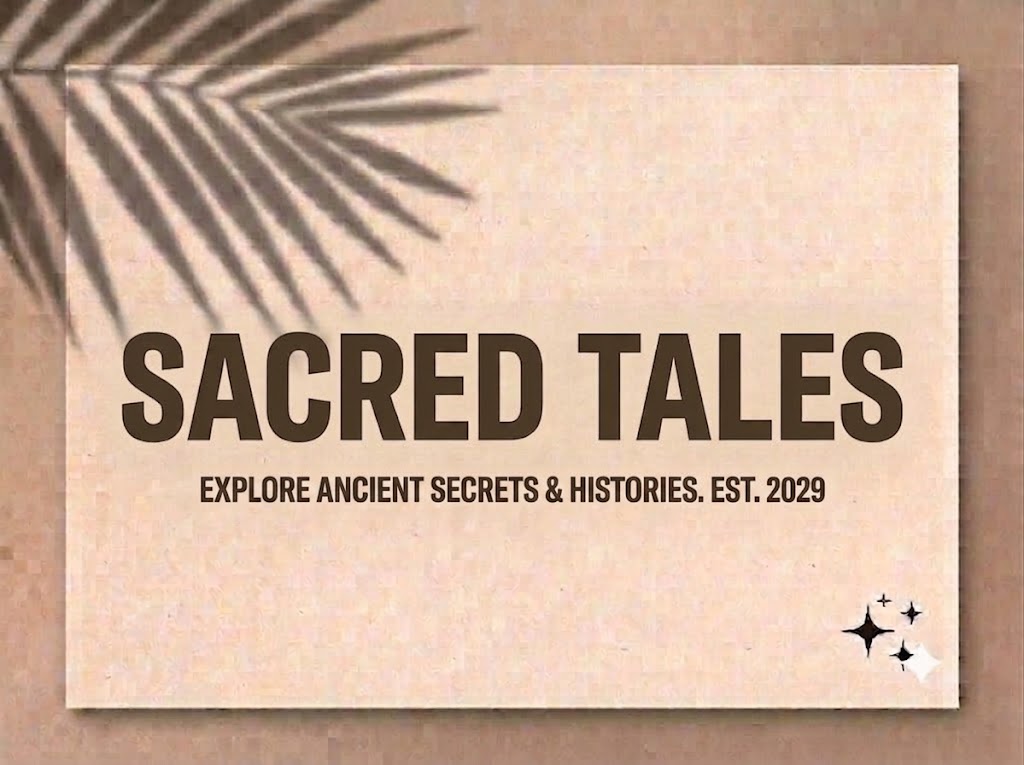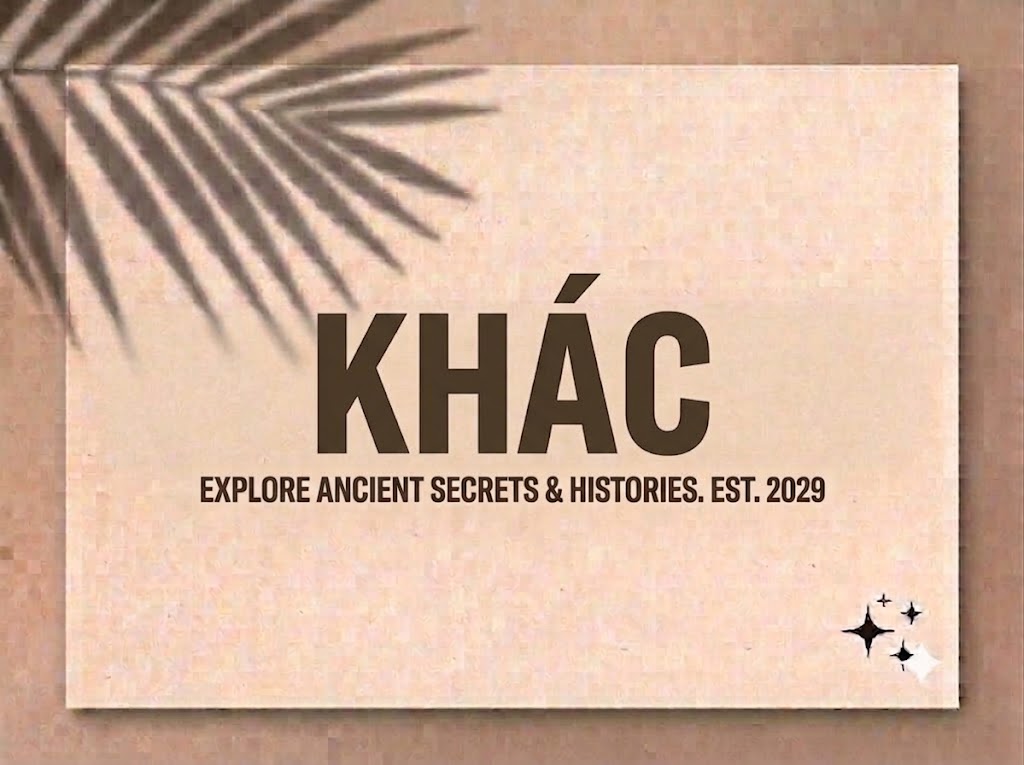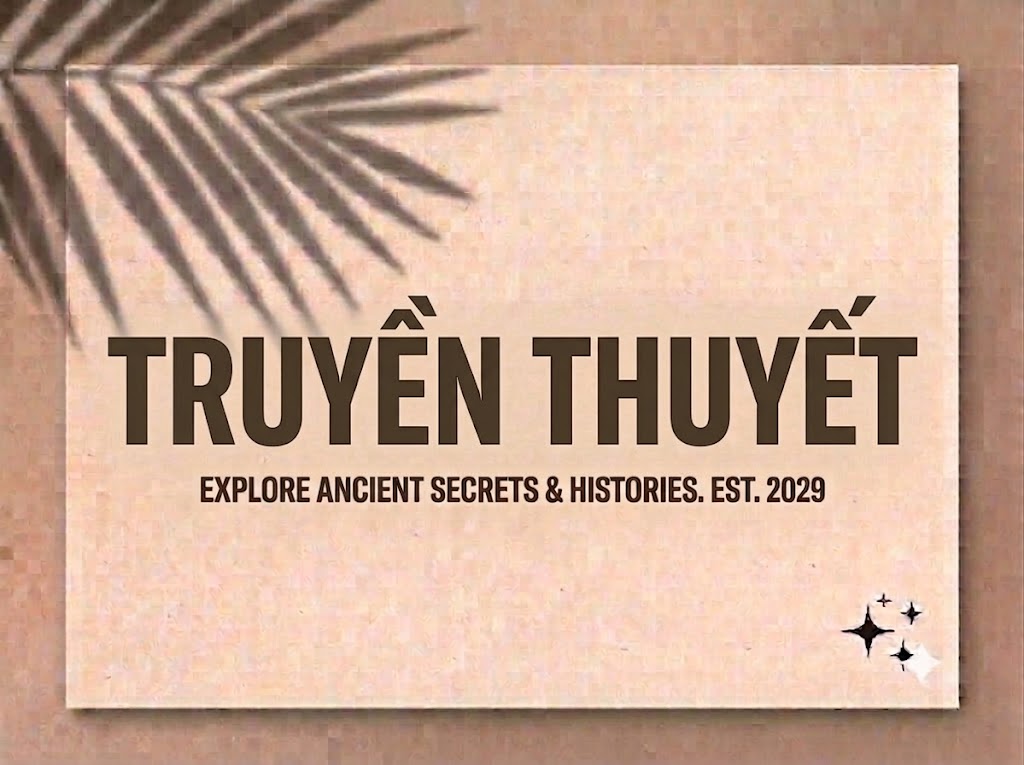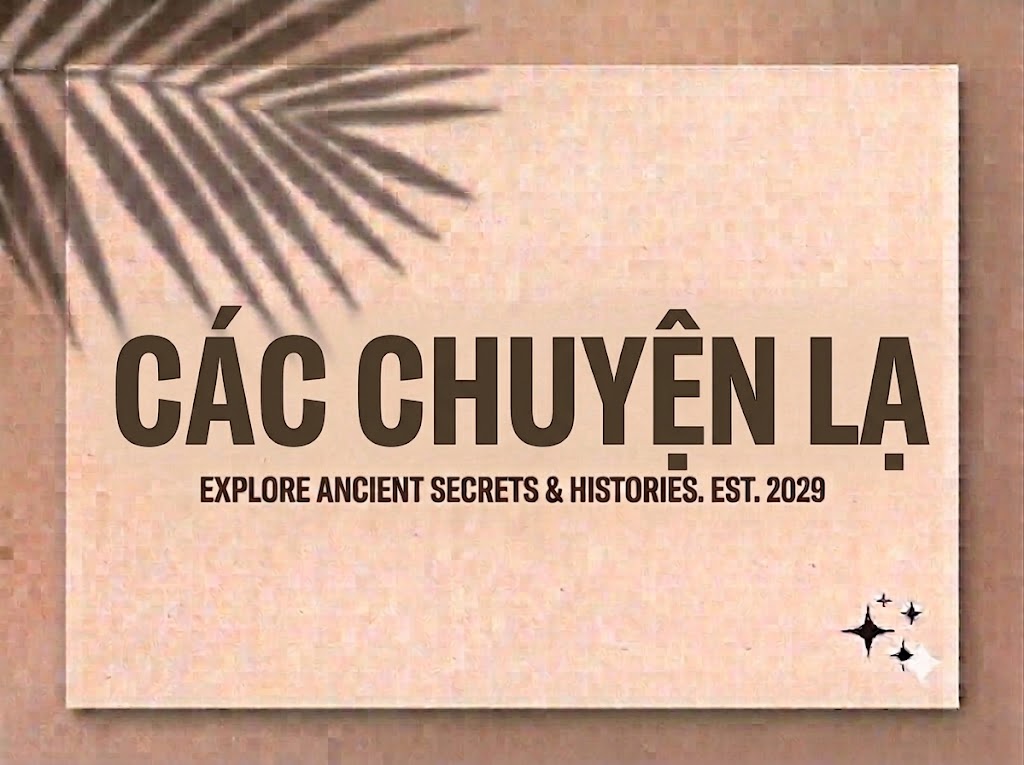
1FTV VIP Bluffolk
Trong bối cảnh thị trường sáng tạo nội dung số ngày càng cạnh tranh gay gắt, một dòng tiêu đề mờ nhạt hay sử dụng các phông chữ đại trà sẽ dễ dàng khiến ấn phẩm của bạn bị lướt qua.
Để chiếm trọn tâm trí người xem ngay từ cái nhìn đầu tiên, các nhà thiết kế luôn ưu tiên lựa chọn những phông chữ hiển thị dáng rộng (extended) với độ dày nét lớn, tạo ra một sức nặng thị giác không thể ngó lơ.
Nếu bạn đang tìm kiếm một giải pháp typographic hầm hố, chắc chắn và mang tinh thần hiện đại, bứt phá cho các dự án truyền thông của mình, thì font 1FTV VIP Bluffolk chính là câu trả lời lý tưởng.
Giới thiệu về font 1FTV VIP Bluffolk
Font 1FTV VIP Bluffolk là một bộ chữ hiển thị không chân (sans-serif) sở hữu cấu trúc hình khối mở rộng bè ngang đầy uy lực và cá tính.
Nhờ cấu trúc kỹ thuật đồng bộ này, phông chữ mang đến khả năng hiển thị vô cùng sắc nét, giúp bạn tự tin ứng dụng trên mọi phần mềm thiết kế và dựng phim chuyên nghiệp mà không lo gặp lỗi vỡ nét hay răng cưa.
Đặc điểm nổi bật của phong cách thiết kế Bluffolk
Sức hút mạnh mẽ nhất của font 1FTV VIP Bluffolk đến từ phom dáng kéo giãn theo chiều ngang (extended wide) kết hợp cùng độ dày nét siêu đậm (heavy bold).
Phông chữ được xây dựng theo định dạng All-Caps (thiết kế viết hoa đồng bộ cho cả hai hàng ký tự trên hệ thống), mang lại sự cân bằng tuyệt đối về mặt cao độ và tạo ra các khối chữ vuông vắn, kiên cố như những bức tường thành.
Các góc ngoài của ký tự được bo cong nhẹ nhàng một cách tinh tế để làm giảm bớt sự thô cứng của hình khối công nghiệp, trong khi các khoảng hở bên trong chữ (counter) vẫn được giữ vuông vức, thông thoáng. Cấu trúc độc đáo này gợi liên tưởng mạnh mẽ đến tinh thần thể thao bứt phá, công nghệ tương lai và xu hướng đường phố hiện đại.
Để phông chữ vận hành mượt mà trên mọi hệ điều hành từ Windows đến macOS, phiên bản font 1FTV VIP Bluffolk đã được tinh chỉnh kỹ lưỡng về mặt thông số kỹ thuật nội tại.
Hệ thống khoảng cách chữ (kerning) và độ giãn dòng đã được tính toán khoa học, giúp các khối chữ siêu đậm khi đứng cạnh nhau luôn giữ được khoảng trống thẩm mỹ lý tưởng, không bị dính nét hay gây cảm giác ngột ngạt khi đọc.
Bên cạnh hệ thống chữ cái viết hoa đồng bộ, font tích hợp đầy đủ hệ thống chữ số từ 0-9 dáng khối dày dặn cùng các ký tự đặc biệt, dấu câu thông dụng (1234567890.:,;'"(!?)+-*/=).
Bản Việt hóa chuẩn chỉnh từ đội ngũ 1FTV giúp các nhà sáng tạo nội dung hoàn toàn yên tâm gõ các cụm từ tiếng Việt có dấu mà không lo bị nhảy font hay lỗi hiển thị ký tự.
Hình ảnh demo thực tế của font 1FTV VIP Bluffolk
Kích thước nhỏ (12pt – 24pt): Dù sở hữu phom dáng mở rộng và nét chữ siêu dày, các khối chữ vẫn đảm bảo độ sắc nét, ngay ngắn và cực kỳ dễ đọc trên giao diện màn hình di động cỡ nhỏ.
Kích thước lớn (36pt – 72pt): Đây là đất diễn hoàn hảo nhất để font chữ phô diễn toàn bộ sức mạnh hình khối hầm hố, tạo tác động thị giác mạnh mẽ nhằm chiếm trọn sự chú ý của người xem cho các dòng headline.
Ứng dụng của font Bluffolk trong thiết kế đồ họa và làm video
Sở hữu nét cá tính hầm hố, vững chãi và cấu trúc hình khối phóng khoáng, font 1FTV VIP Bluffolk mở ra không gian ứng dụng vô cùng rộng lớn cho các dự án truyền thông và marketing:
Làm tiêu đề cho video ngắn (TikTok, Reels, Shorts): Dáng chữ khối ngang siêu đậm này là lựa chọn tuyệt vời để làm các cụm keyword chính giật tít ở phần mở đầu video. Độ bắt mắt của chữ giúp giữ chân người xem lướt chậm lại ngay lập tức, đồng thời hiển thị cực kỳ nổi bật trên các khung hình đứng 9:16 của thiết bị di động.
Thiết kế ảnh thu nhỏ YouTube (Thumbnail): Đây là vũ khí hạng nặng để tăng tỷ lệ nhấp chuột (CTR) cho các kênh thuộc chủ đề gaming, thể thao điện tử (esports), review xe, đồ công nghệ hoặc các nội dung hành động, thử thách ngắn nhờ độ dễ đọc rất cao từ khoảng cách xa.
Poster và Banner quảng cáo ngành giải trí, thể thao: Cực kỳ hoàn hảo cho các poster giải đấu game, banner câu lạc bộ gym, fitness, đua xe hoặc các sự kiện âm nhạc điện tử sôi động của giới trẻ.
Nhận diện thương hiệu phong cách Streetwear: Phù hợp làm logo dạng chữ khối, biểu ngữ quảng cáo, hoặc thiết kế artwork in ấn trên áo thun, bao bì cho các local brand thời trang đường phố hướng tới sự bụi bặm, nam tính và phá cách.